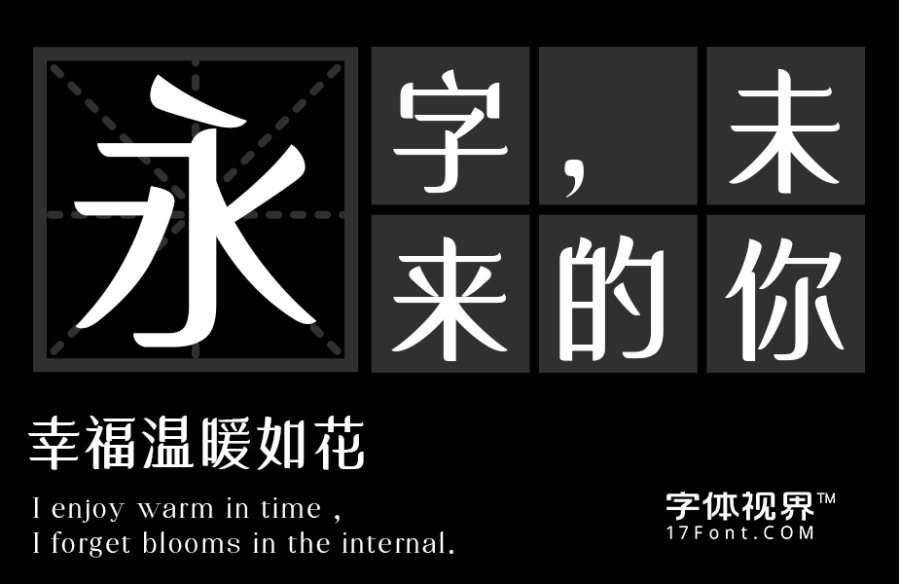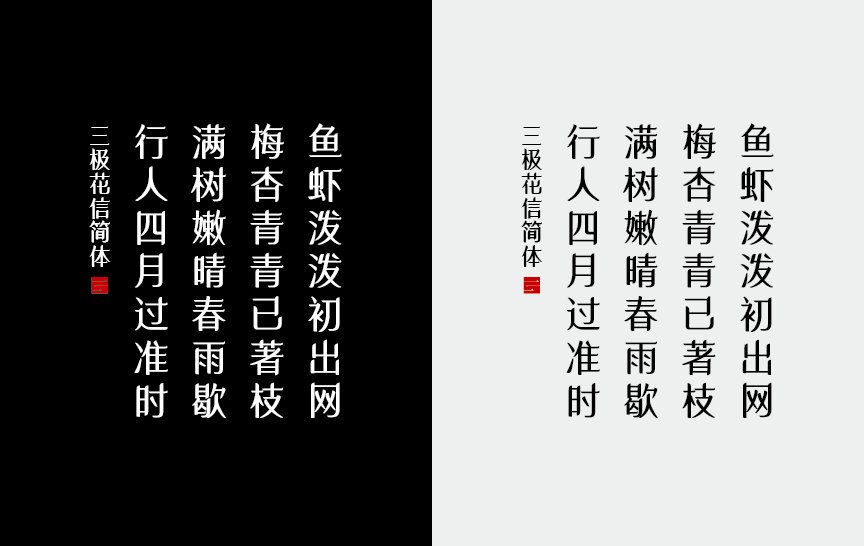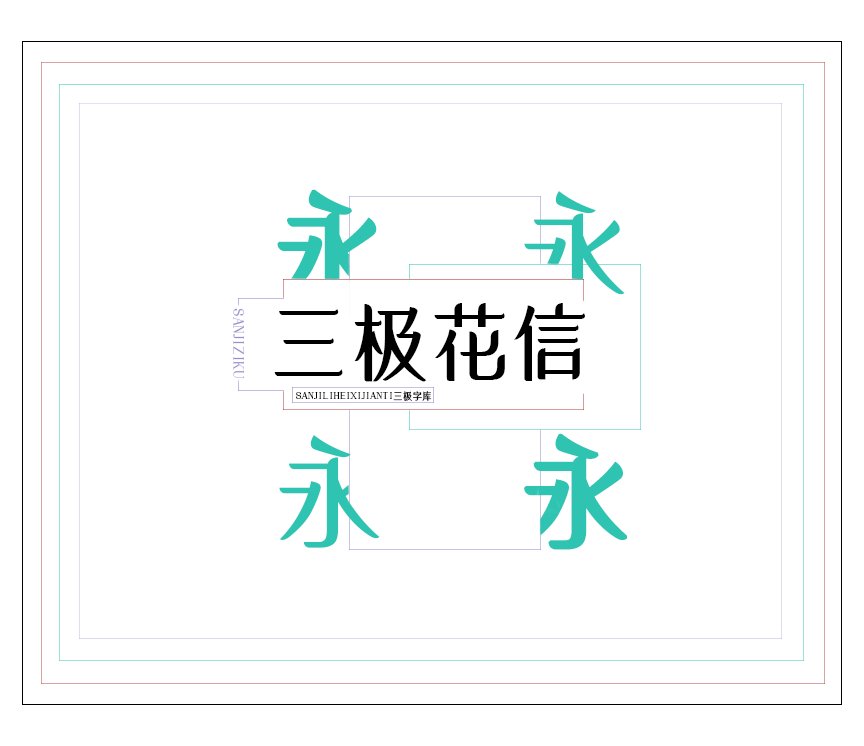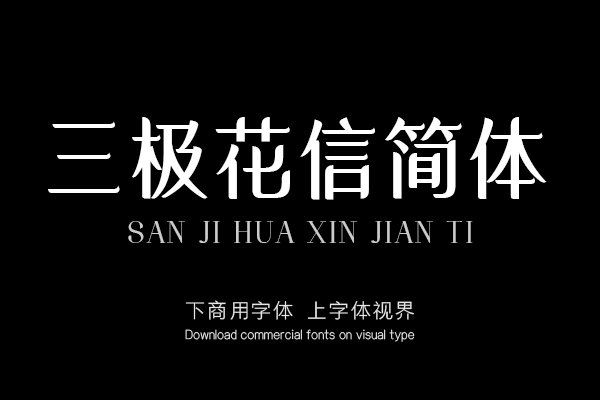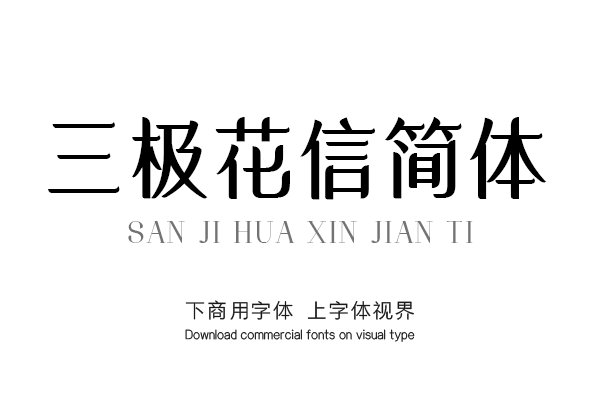
三极花信简体是具有典雅气质的风格化黑体作品。兼具了黑体的简洁和宋体的雅致特征。 整体字形方正,刚柔相济,优雅大方。其横竖笔画横纵,横竖笔画粗细反差较大......购买须知:“下载服务费”与“字体VIP”所获得字体 仅用于个人非商用, 商用请联系付费授权。本字体为电脑用字,手机没有root权限不支持直接手机换字(手机如何root,请自行百度搜索教程)。购买前请先 了解清楚后再付款 ,字体为虚拟产品无法回收 一旦购买不支持退款。